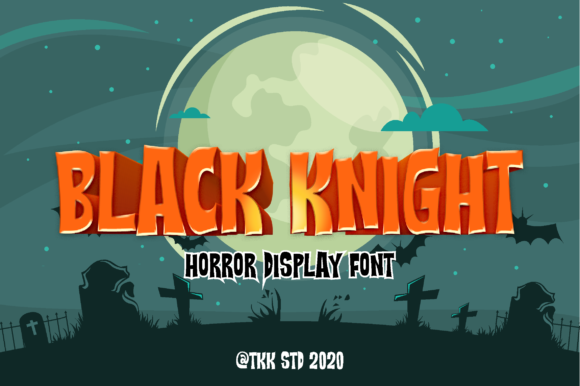
Black Knight - прыгучий и причудливый шрифт.
Он добавит свежести и современности вашему дизайну.
Добавьте этот уникальный шрифт дисплея к каждой из ваших творческих идей и заметьте, как это делает их выделяющимися!